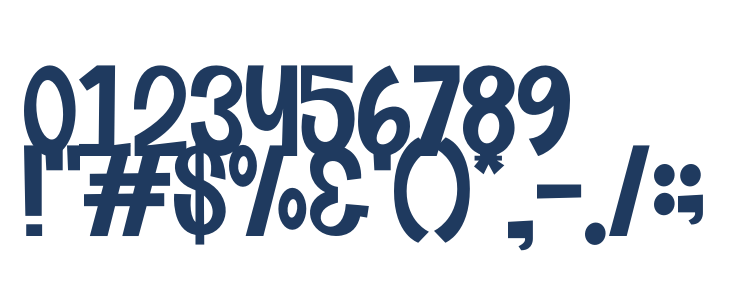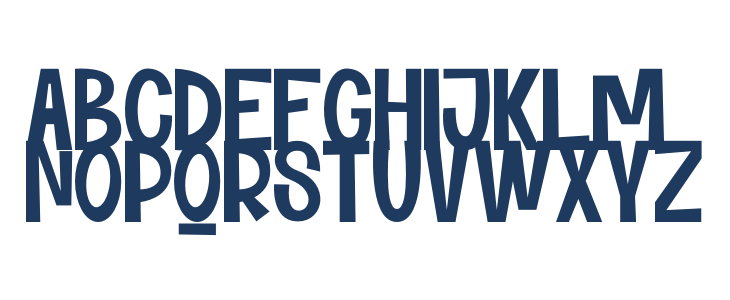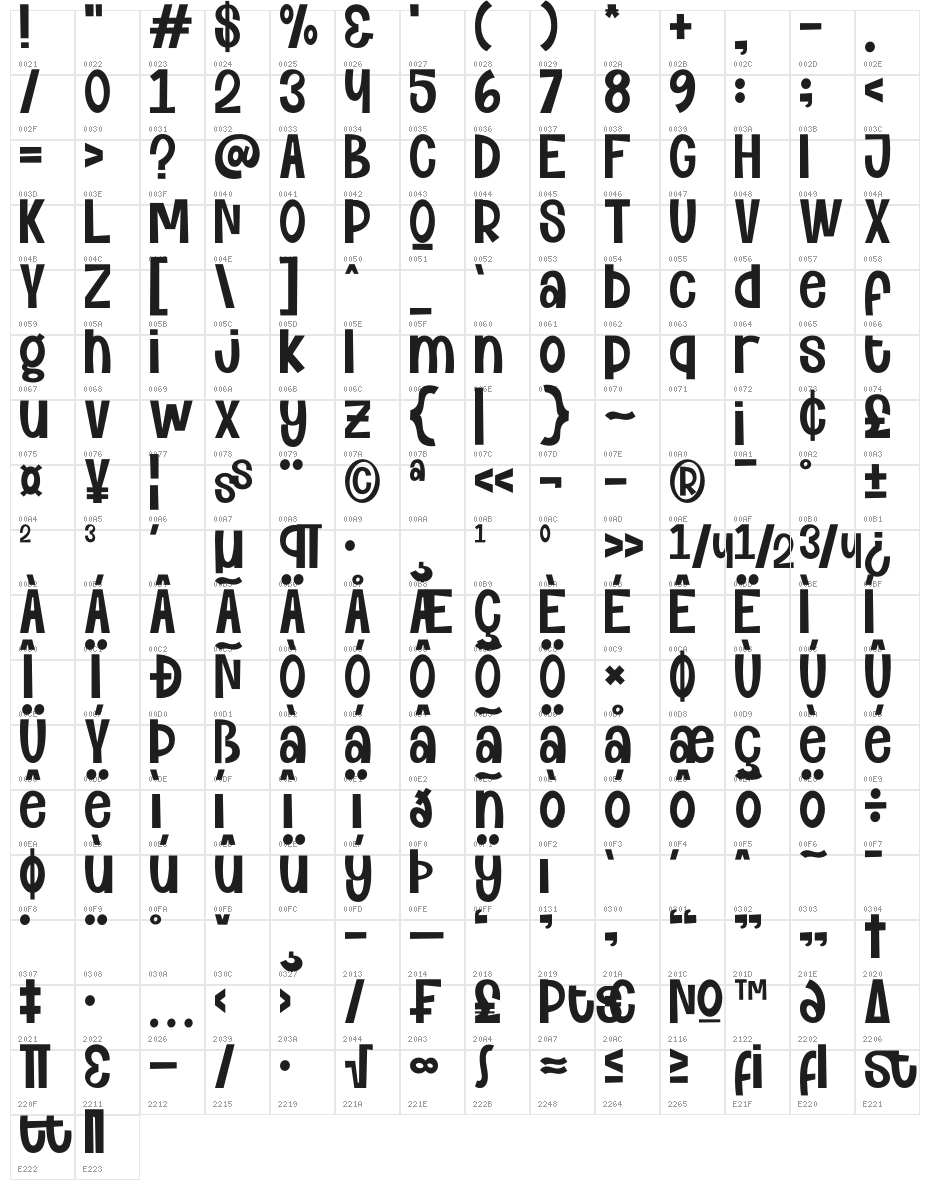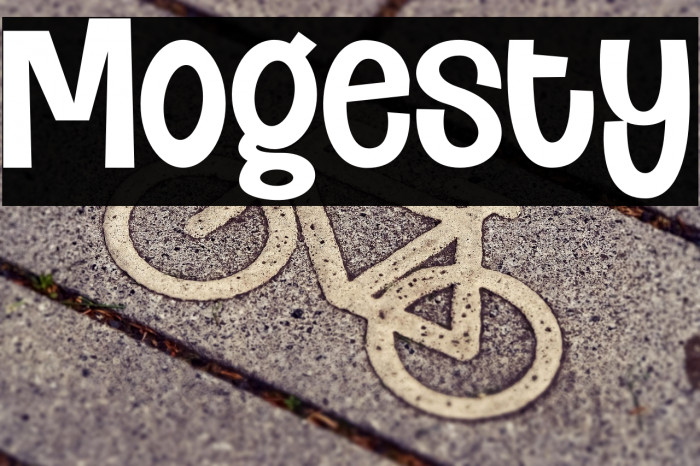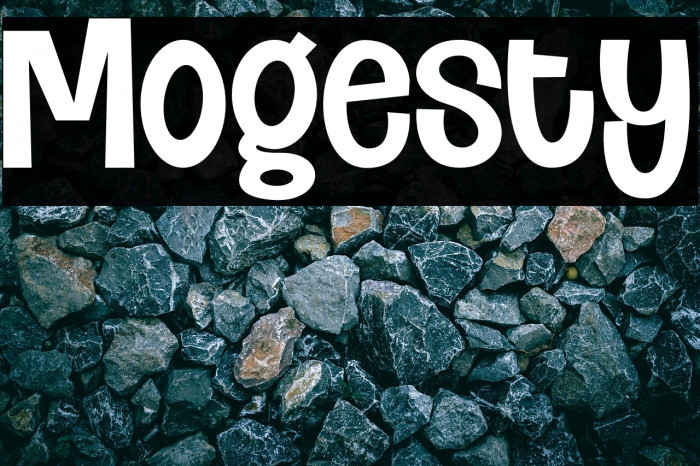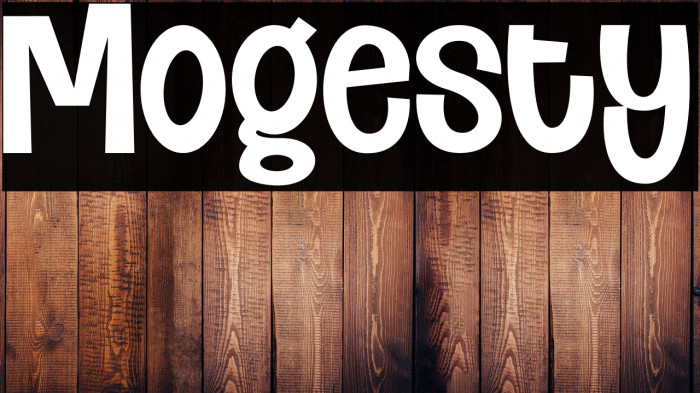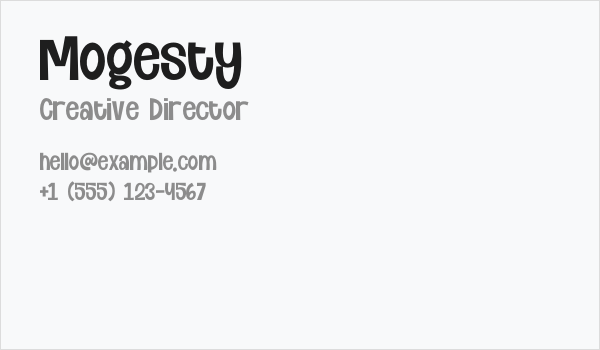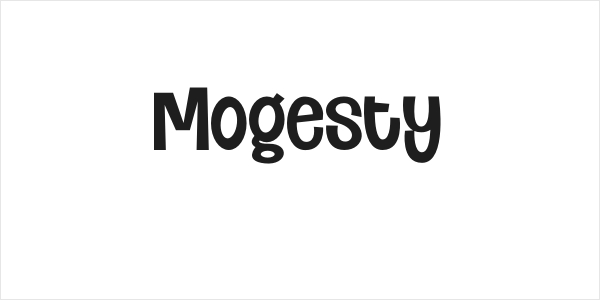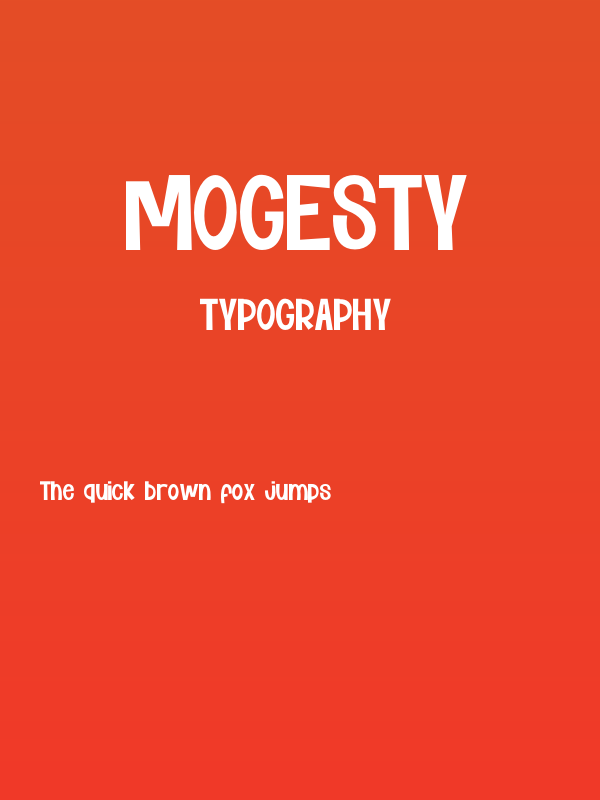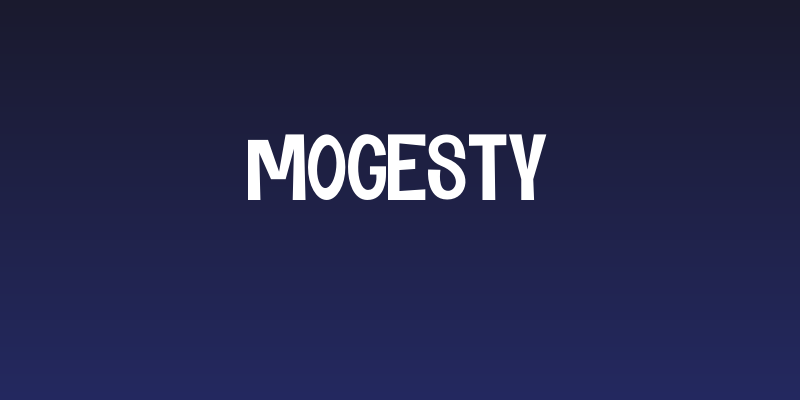
Mogesty Font
| Stile generale | Playful, Decorative, Modern |
| Caso d'uso | Headlines, Posters, Logos, Invitations |
| Progetti proposti | Children’s books, posters, party invitations, branding for playful or creative businesses, headlines. |